Google Docs, Slides에서 PDF로 내보내기 했을 때 한국어 글꼴이 깨지는 이슈
Google Drive에서 작성한 문서를 PDF로 내보내기 했을 때,
한국어 글꼴이 나눔고딕으로 자동 변환되는 이슈가 있습니다.
문제
작성할 땐 고딕체처럼 나오는데,
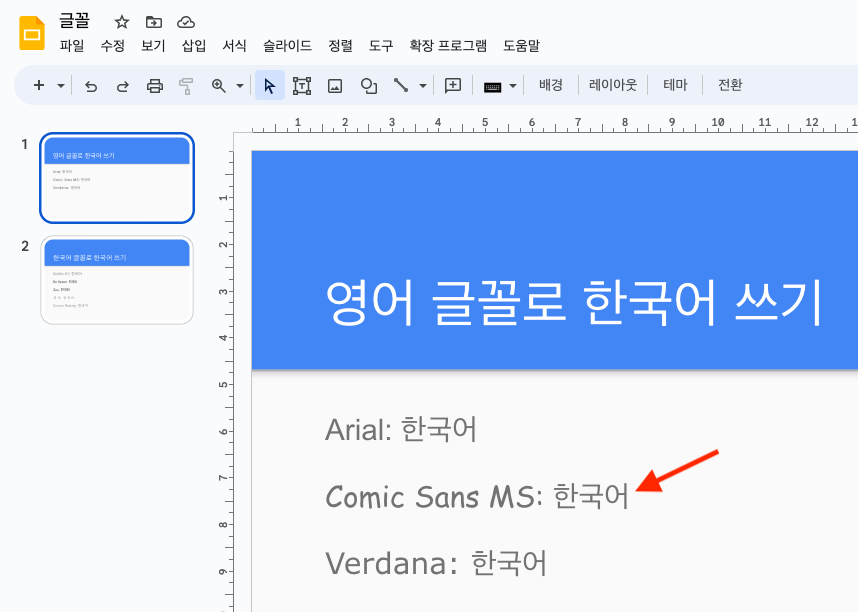
PDF로 내보내기 하면, 모두 나눔고딕으로 나옵니다.
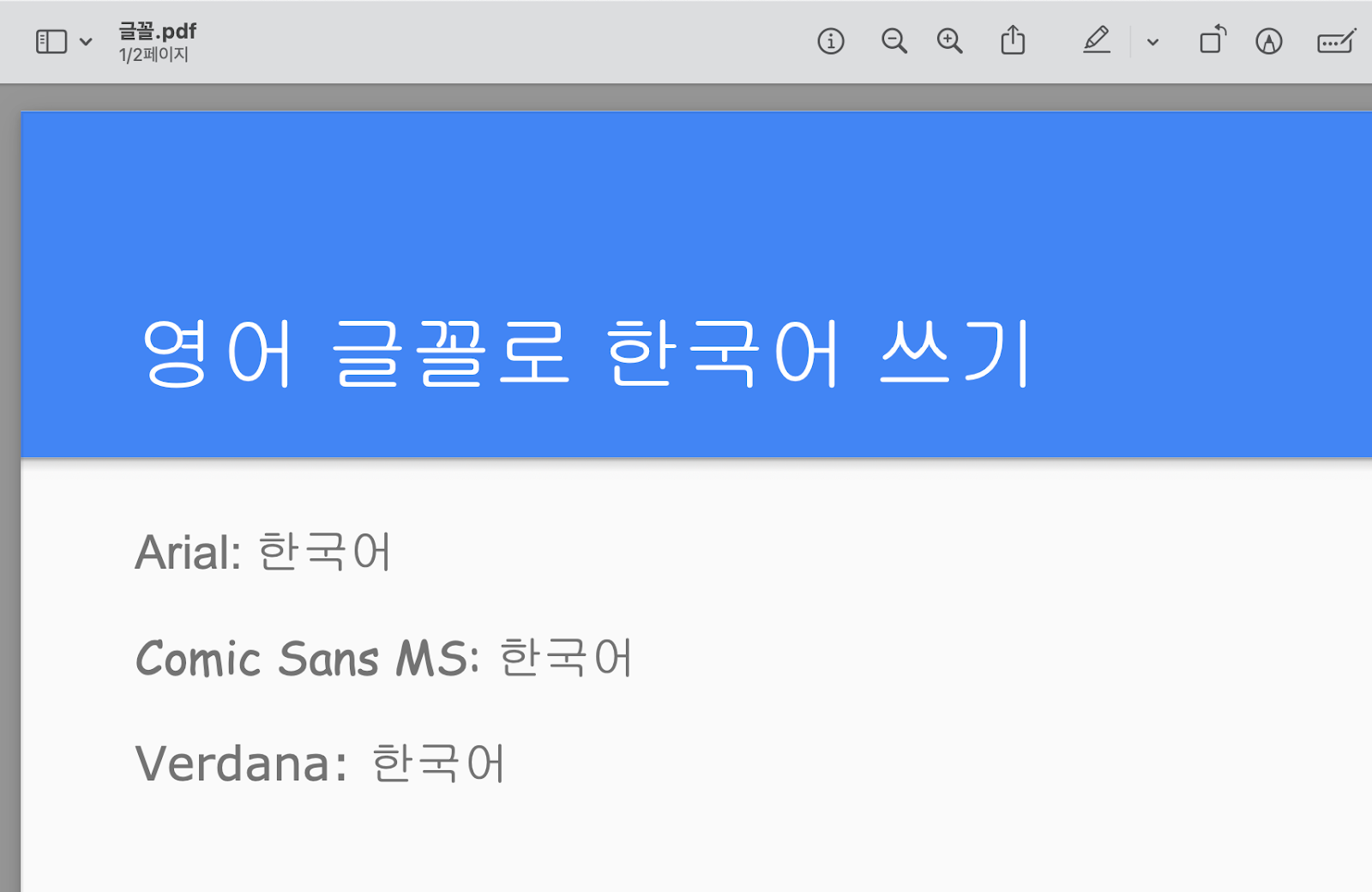
창을 두개 띄워놓고 비교하면 차이점을 더 잘 확인할 수 있습니다.
왼쪽은 Google Slide, 오른쪽은 내보내기한 PDF 파일입니다.
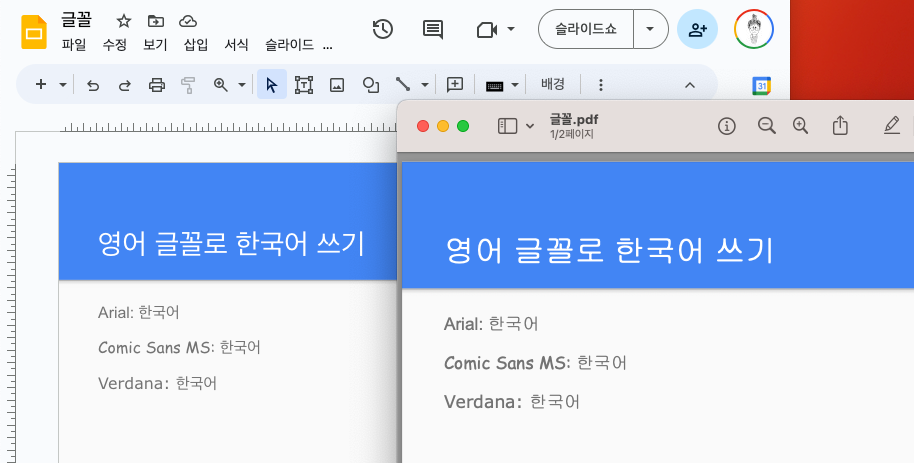
해결 방법
글꼴 > 글꼴 더보기 를 클릭합니다.
[문자: 한국어]로 필터링합니다.
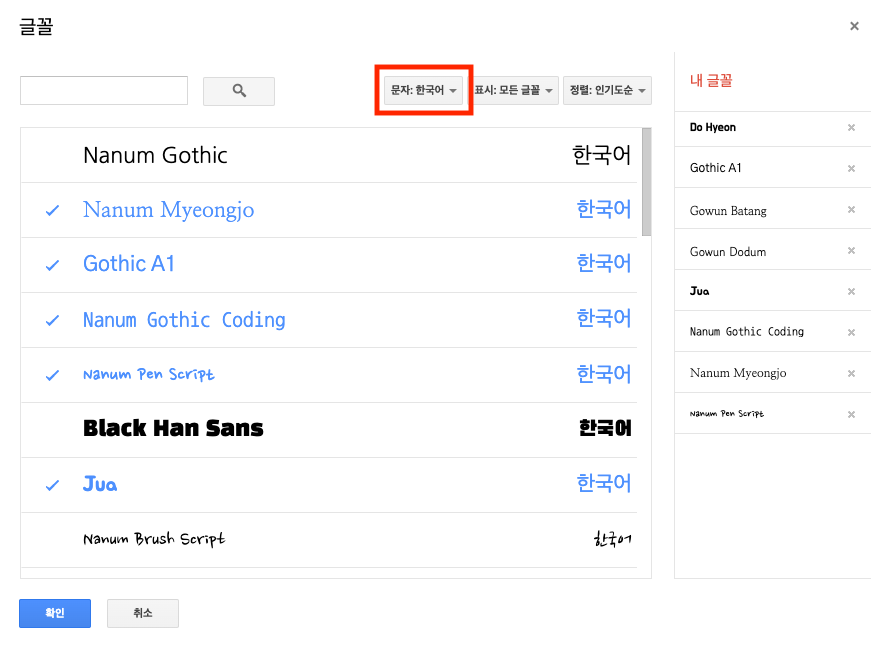
[문자: 한국어]로 필터링했을 때 나오는 글꼴로 한국어를 입력하고 PDF로 출력하면 글꼴이 정상적으로 나오는 것을 확인할 수 있습니다.
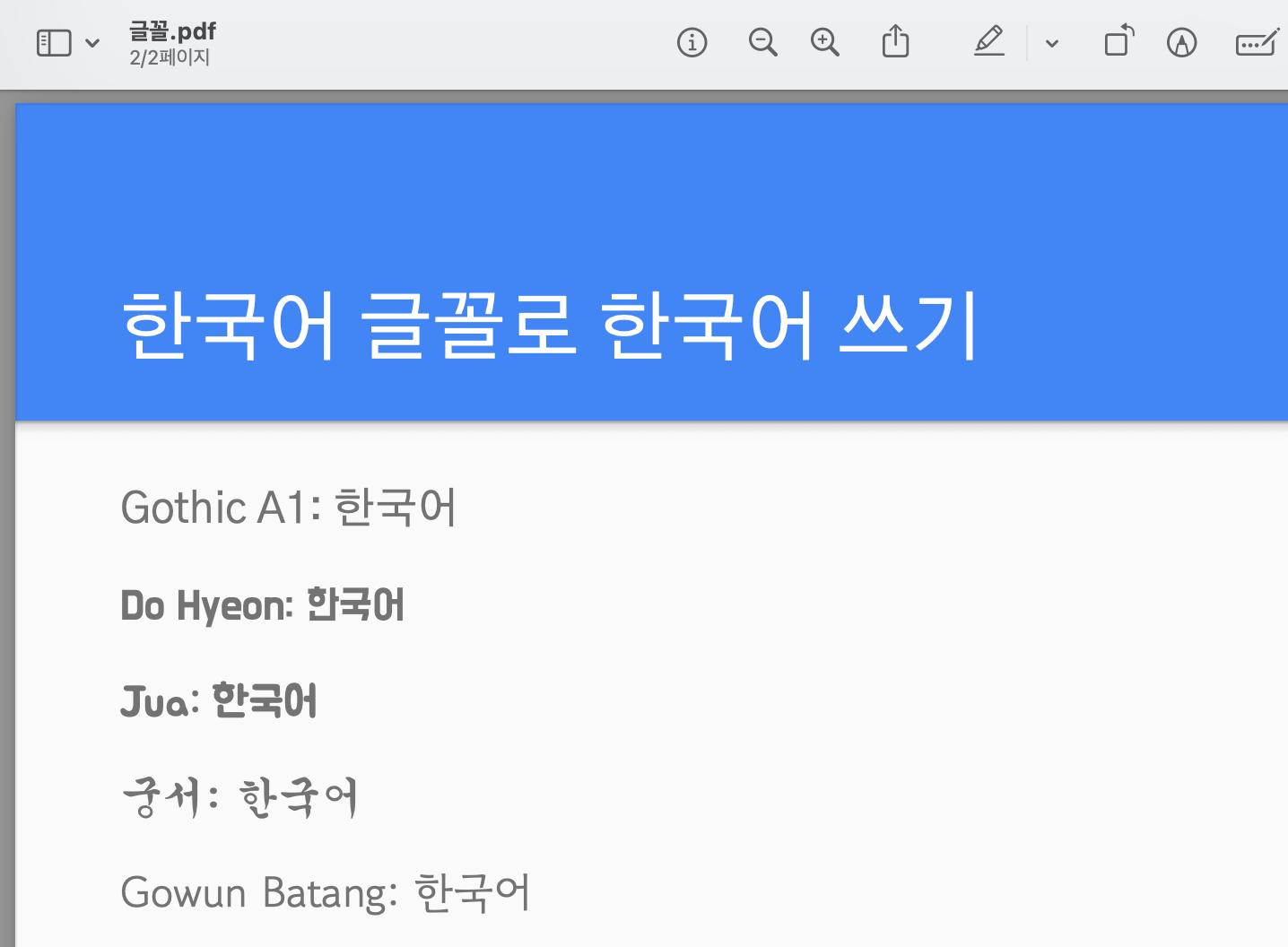
비교해보면 글꼴이 동일하게 나오는 것을 확인할 수 있습니다.
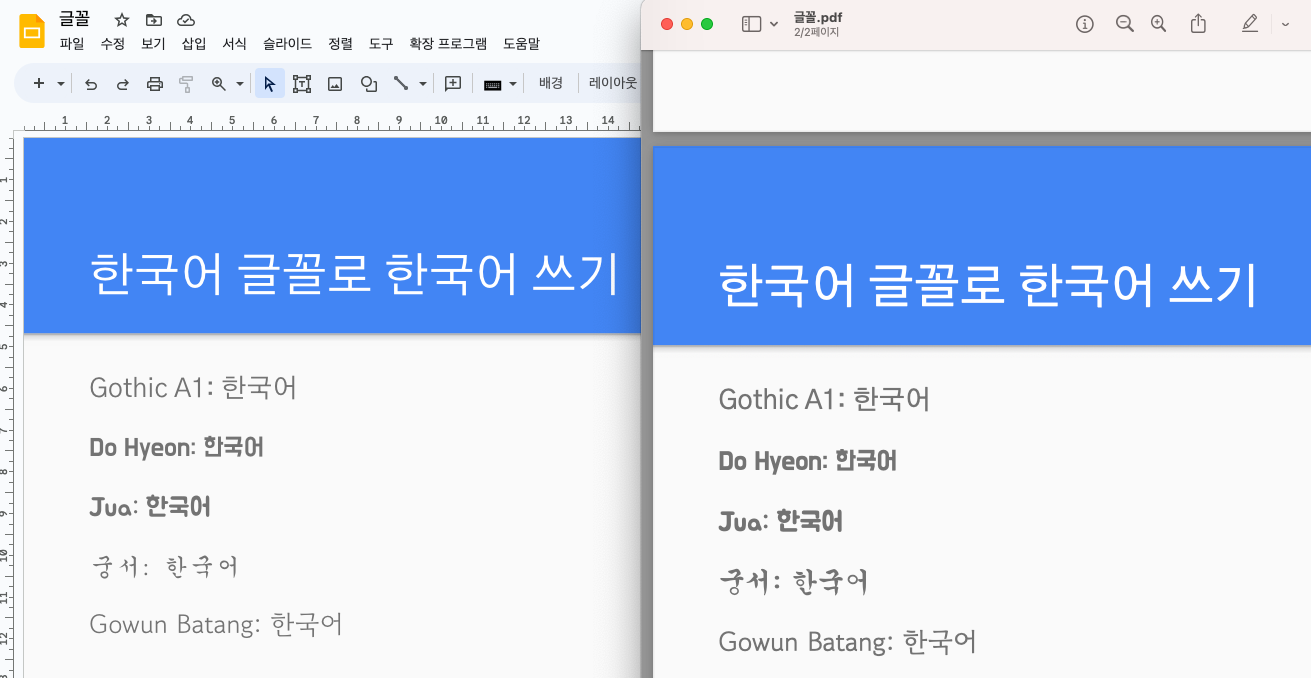
Google Slide 뿐 아니라, Google Docs에서도 [문자: 한국어]로 필터링하면 원하는 글꼴대로 내보내기 할 수 있습니다.
앞으로 Google Workspace에서 더 다양한 한국어 글꼴을 지원해주면 좋겠네요 :)
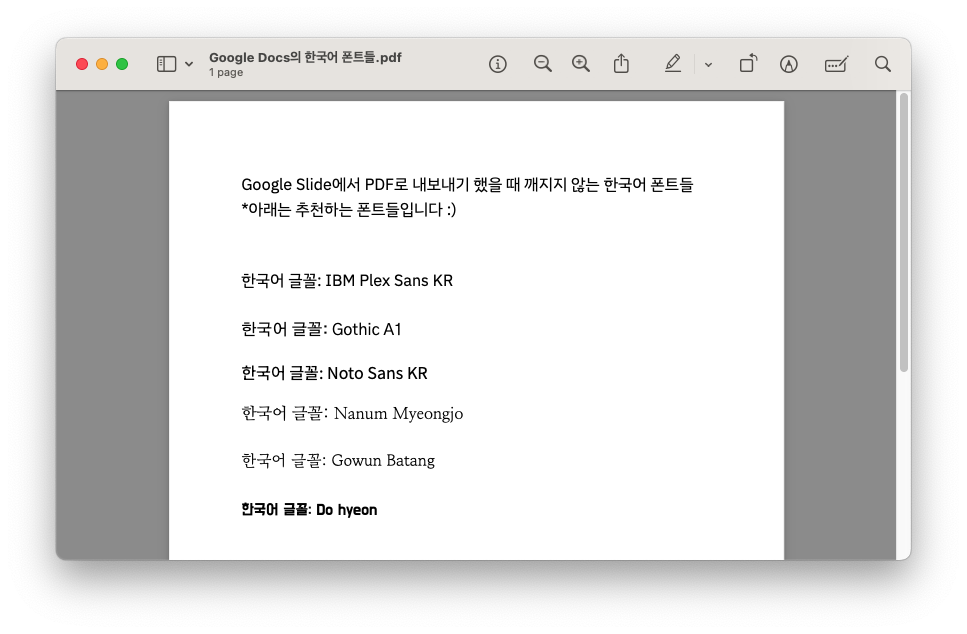
개인적으로 Arial이나 Roboto를 대체할 정도로 비슷한 한국어 글꼴은
IBM Plex Sans KR, Gothic A1 인 것 같습니다 :)